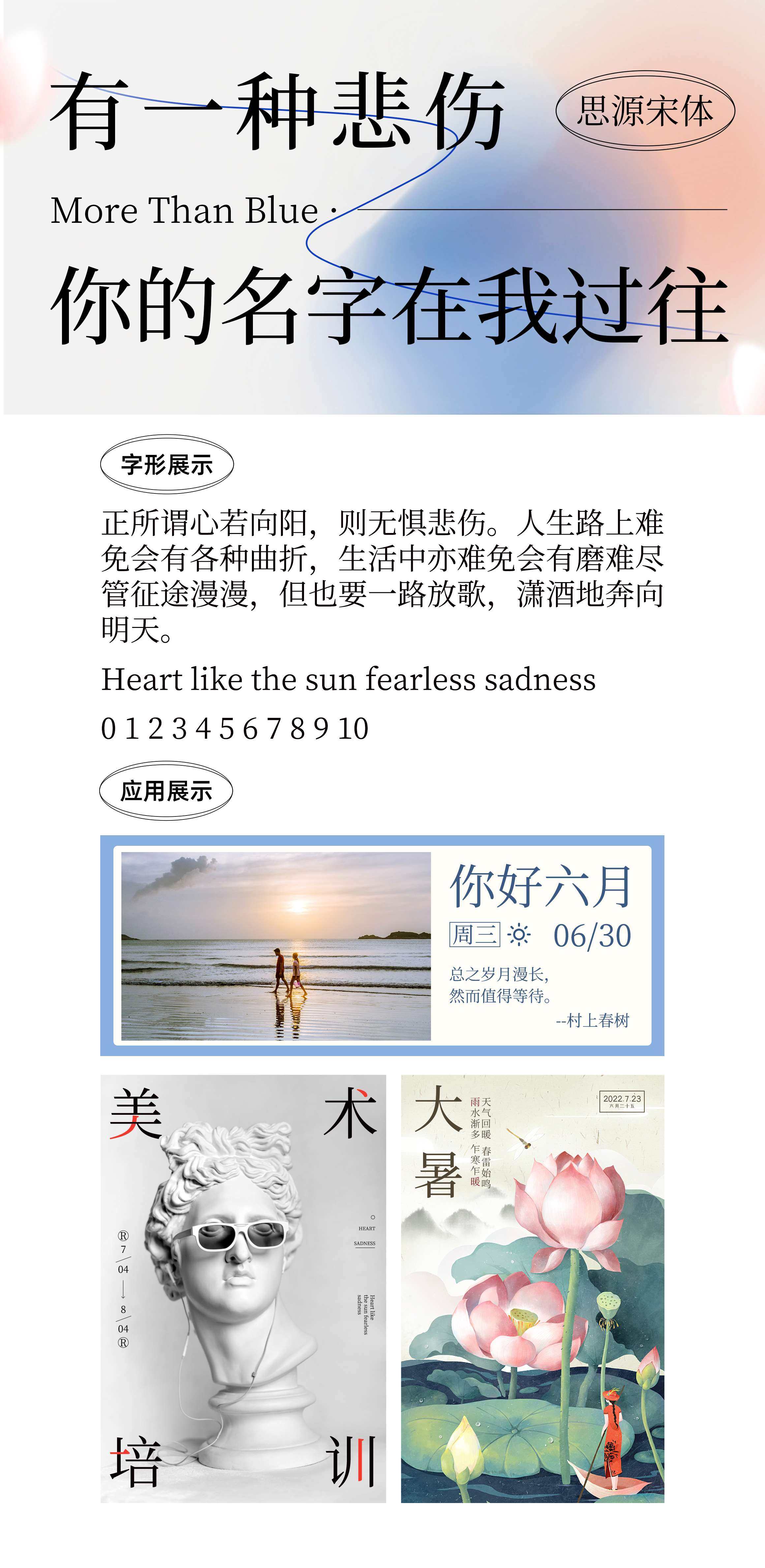
思源宋体
Adobe×Google
思源宋体是 Adobe Type 发布的最新泛 CJK 字体,它是对应于思源黑体的宋体字体;我们发布这两种字体是为了响应统一设计的需求,以服务于东亚 15 亿人口。 思源宋体也和它的兄弟字体思源黑体一样针对屏幕显示进行了优化,但前者具有截然不同的风格,适合用于文学性较强的文本或优雅、时尚的标题。它的打印效果也非常优美。通过 Typekit 同步字体可让您使用同一种字体即时呈现多种语言,并且在任何带有字体选择菜单的桌面应用程序中使用这些字体。